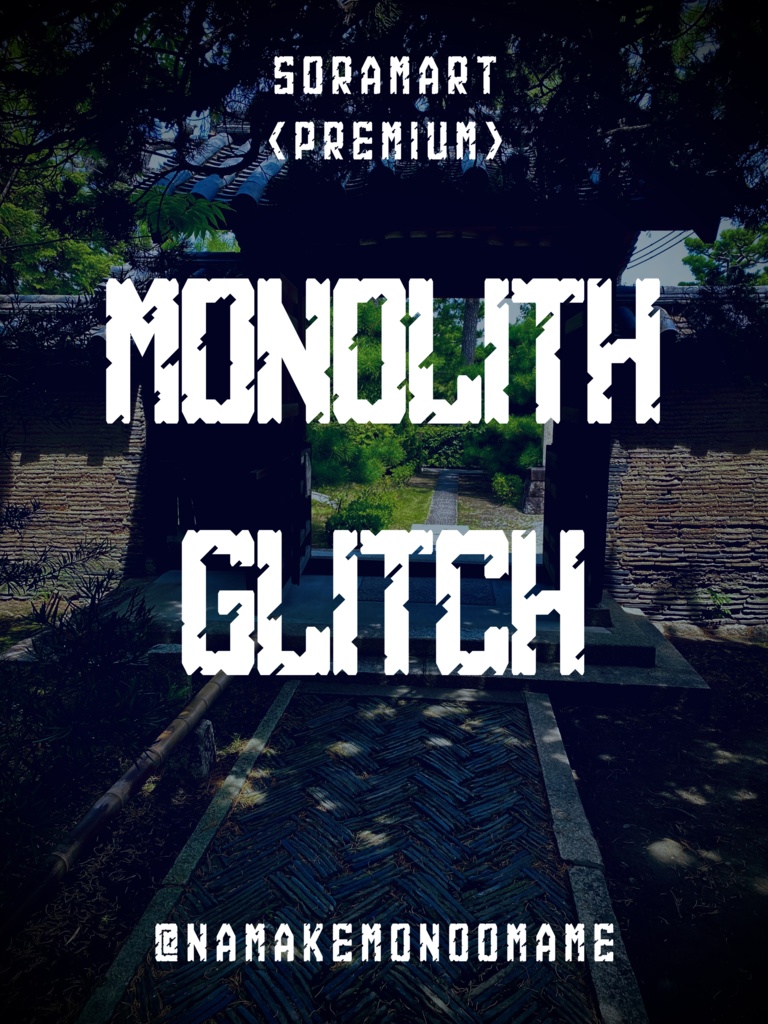
そらマートフォントデータ”Monolith Glitch”Digital2,500 JPY加入购物车Buy a GiftAbout Giftシンプルスタイルの縦長フォントにかすれ加工を施した "Monolith Glitch" です。 「TrueTypeフォントファイル」という形式です。 ダウンロードした後、Zipファイル内のデータをインストールしてお使いください。 このフォントは商用利用可となっております。 お客様の制作・創作活動のお役に立てれば幸いです。 ※使用上の注意事項などは、添付のReadmeをお読みください。 ※このフォントは、有料販売専用商品です。そらマートVisit FANBOX!Fontsフォントデータ”Mars Invader Balloon”そらマート2,500 JPYFontsフォントデータ”Mars Invader Wide”そらマート0 JPYFontsフォントデータ”Mars Invader”そらマート0 JPYFontsフォントデータ”Rock Cut Serif”そらマート2,500 JPYFontsフォントデータ”Rock Cut Drop Wide”そらマート2,500 JPYFontsフォントデータ”Rock Cut Drop”そらマート2,500 JPYFontsフォントデータ”Longtail Sans Serif Slashed”そらマート2,500 JPYFontsフォントデータ”Longtail Sans Serif Bold”そらマート2,500 JPYFontsフォントデータ”Longtail Sans Serif”そらマート2,500 JPYFontsフォントデータ”Pretty Commando”そらマート2,500 JPYFontsフォントデータ”Abyss Dive Punk Retro”そらマート2,500 JPYFontsフォントデータ”Abyss Dive Punk Wide”そらマート2,500 JPYFontsフォントデータ”Abyss Dive Punk”そらマート2,500 JPYFontsフォントデータ”Emerald Sphere Sprite”そらマート2,500 JPYFontsフォントデータ”Emerald Sphere Long”そらマート2,500 JPYFontsフォントデータ”Emerald Sphere”そらマート2,500 JPYFontsフォントデータ”Monolith Formula”そらマート2,500 JPYFontsフォントデータ”Rolling Cute”そらマート2,500 JPYFontsフォントデータ”Tricky Wire Merge”そらマート2,500 JPYFontsフォントデータ”Tricky Layer Wide”そらマート2,500 JPY查看更多